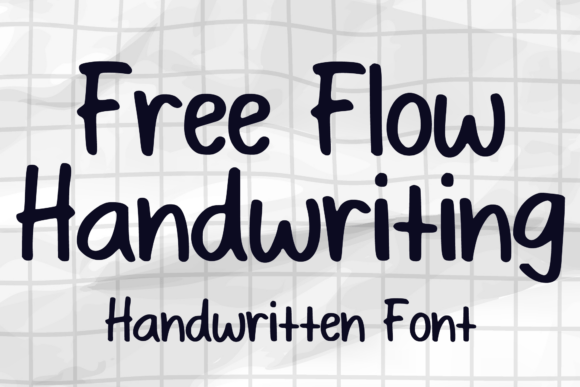
Free Flow Handwriting
Free Flow Handwritingのような高品質の素材をお探しの場合、このプレミアムパッケージはクリエイティブなプロジェクトに素晴らしい選択です。
POD(オンデマンド印刷)製品、結婚式の招待状、またはソーシャルメディアのグラフィックを作成している場合でも、Free Flow Handwritingは理想的です。